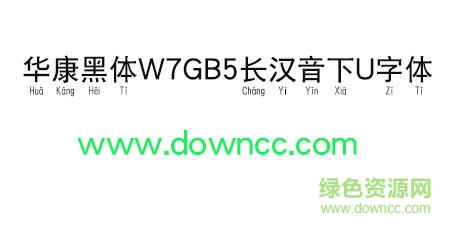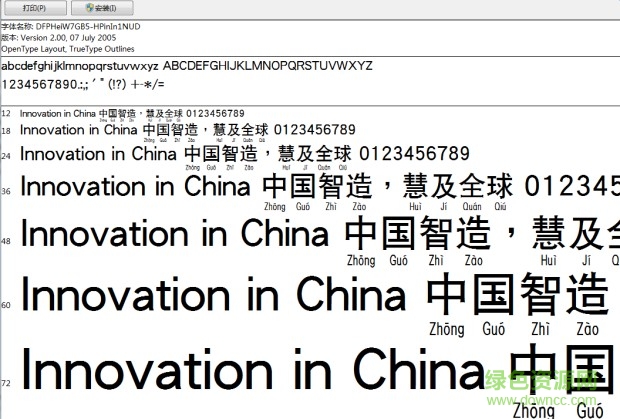
華康黑體W7GB5長(zhǎng)漢音下U字體是一款華康字體庫(kù)的個(gè)性字體,該字體可應(yīng)用于正文標(biāo)題、印刷包裝、平面設(shè)計(jì)、辦公學(xué)習(xí)、繪畫(huà)創(chuàng)作等領(lǐng)域,到目前為止都廣受用戶的好評(píng),需要的朋友就請(qǐng)來(lái)綠色資源網(wǎng)下載使用。